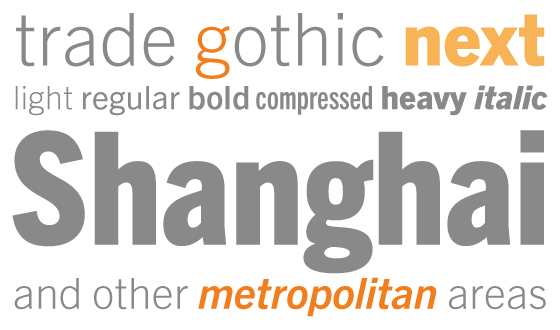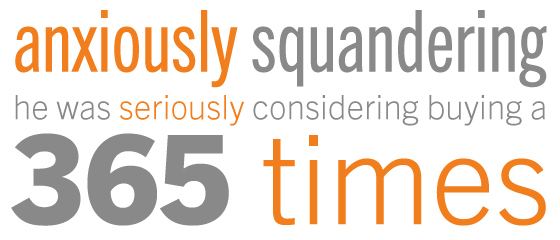
Trade Gothic Next (Linotype)
Linotype hat die klassische Schrift Trade Gothic® von Grund auf überarbeitet. Entdecken Sie unsere neueste, leistungsstarke Schriftfamilie: Trade Gothic Next! Die ursprüngliche Trade Gothic geht auf das Jahr 1948 zurück, als Jackson Burke Leiter der Abteilung Typografische Entwicklung bei Linotype war. Im Verlauf der Jahre wurde die Schriftfamilie erweitert, jedoch ohne die Strukturen aller enthaltenen Mitglieder zu vereinheitlichen. Der heutige künstlerische Leiter von Linotype, Akira Kobayashi, optimierte die Trade Gothic nun erheblich, indem er die Details der Schrift, wie zum Beispiel die Abschlüsse, Linienenden, Zeichenabstände und Unterschneidungen, überarbeitete. Unter seiner Leitung wurde sie mit den Schnitten Compressed und Heavy versehen, um ihr als Titelschrift mehr Ausdruck zu verleihen, und die Regular-Version wurde zur Optimierung im Werksatz aktualisiert.
Ich weiß genau was du meinst und das ist auch mein Kritikpunkt.
Gerade C, O und die Null der Trade Gothic Bold Condensed #20
vermisse ich sehr - in Headlines unschlagbar! Andererseits passte
dieser Schnitt nie zu den anderen Schnitten und in Kombination
sah das mitunter sehr komisch aus. Insofern begrüße ich die Ver-
einheitlichung und den Ausbau der Trade Gothic Next.
Wo gehobelt wird fallen leider auch Späne ...
Genau das hätte ich jetzt auch gesagt; irgendwie schade, dass sie so «glatt» geworden ist. Aber ist vermutlich praktischer so. Hm.
Solange man die alten Schnitte nicht mischen muss ist alles
okay - aber wenn man mischt sieht es schnell sehr komisch aus.
Hier ein Beispiel – oben die Trade Gothic Bold Condensed 20
und unten die Trade Gothic Condensed 18.
Ich finde O, G, p, g, e und die Ziffern gehen gar nicht zusammen!